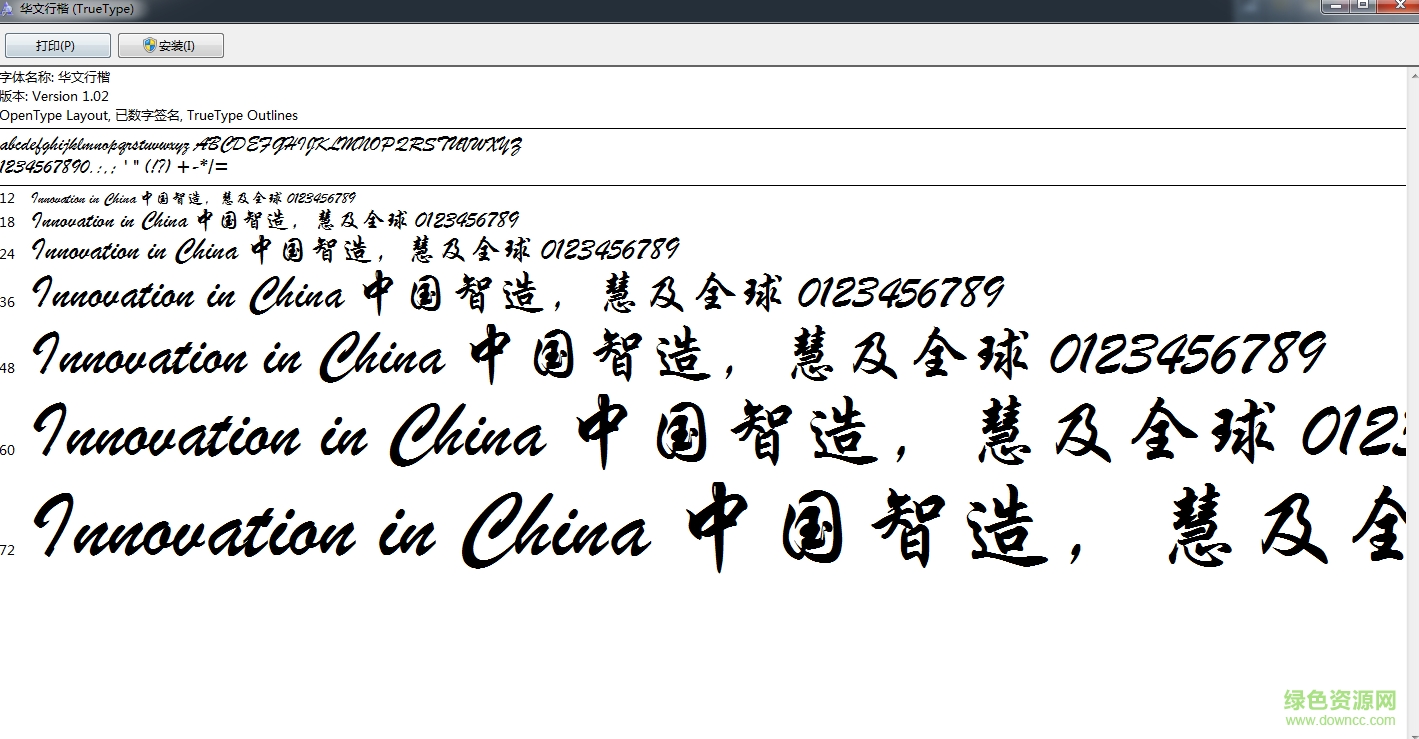
stxingkai sc bold字體
stxingkai sc bold字體又叫華為行楷粗體,是一款粗重漂亮的行楷字體,該字體起承轉(zhuǎn)合流暢瀟灑,十分漂亮得體,喜歡的朋友快來(lái)綠色資源網(wǎng)下載吧!
行楷與楷書字體用筆區(qū)別
楷書的起筆、行筆、收筆等過(guò)程中,提筆、頓筆、轉(zhuǎn)筆等運(yùn)用要求嚴(yán)格,書寫要平穩(wěn),有輕重提按、入鋒回筆等具體要求。筆數(shù),筆順,一定的行筆規(guī)則是不可以隨意改變的。
行楷的用筆則靈活、方便,一般不需要逆鋒、頓筆、停筆等嚴(yán)格的運(yùn)筆,不強(qiáng)調(diào)用筆中更多的提按、筆畫形態(tài),只要求筆道流暢,使轉(zhuǎn)合理,行筆巧妙。